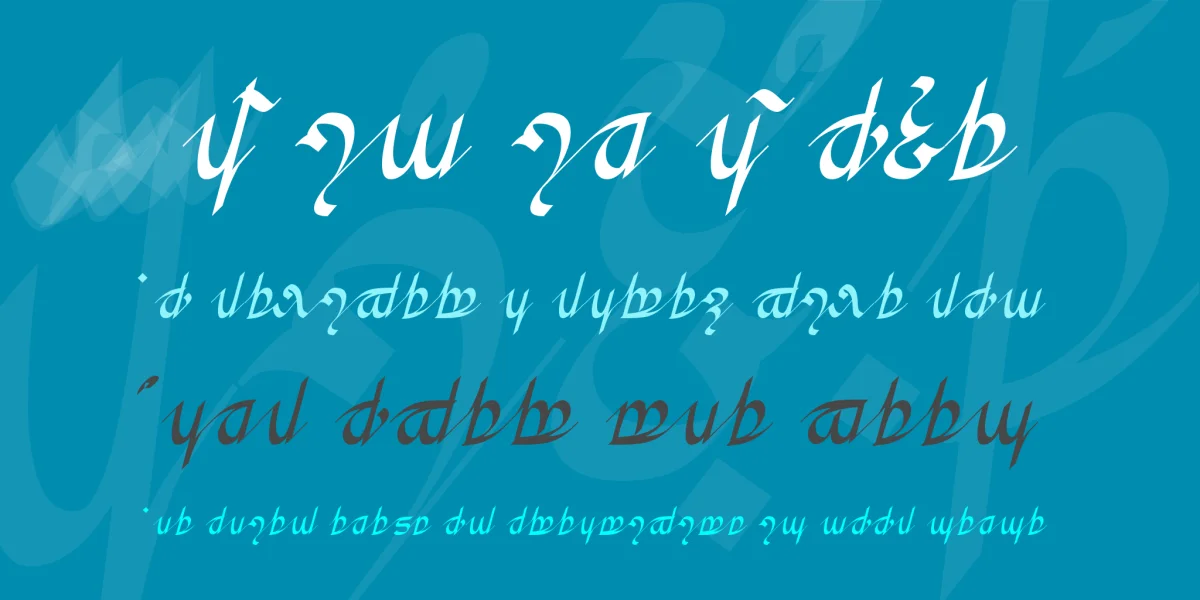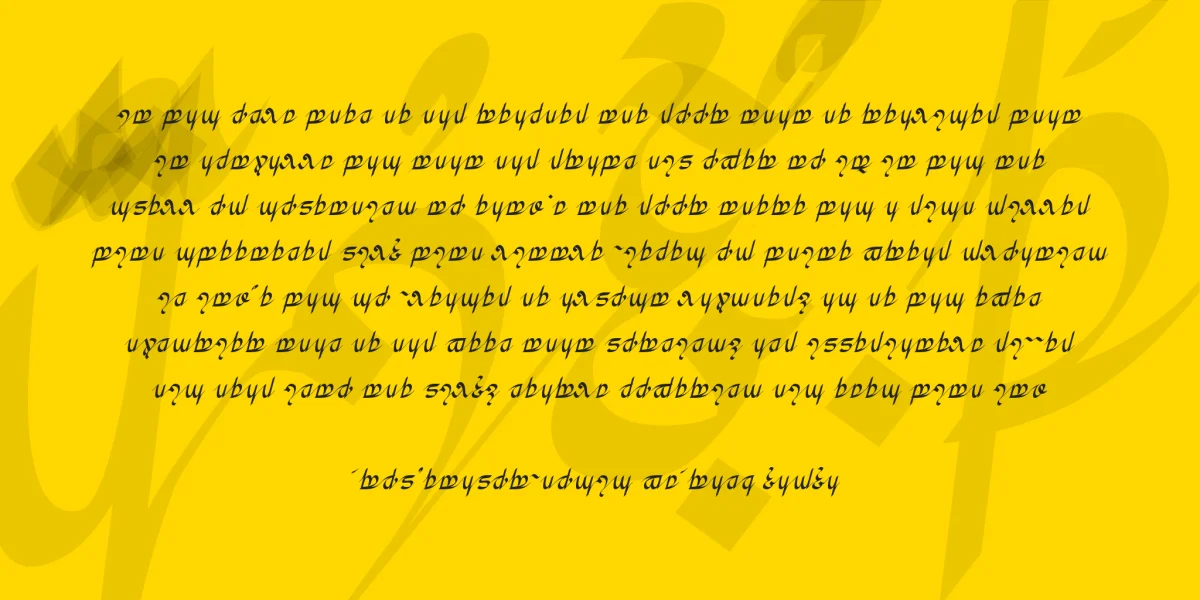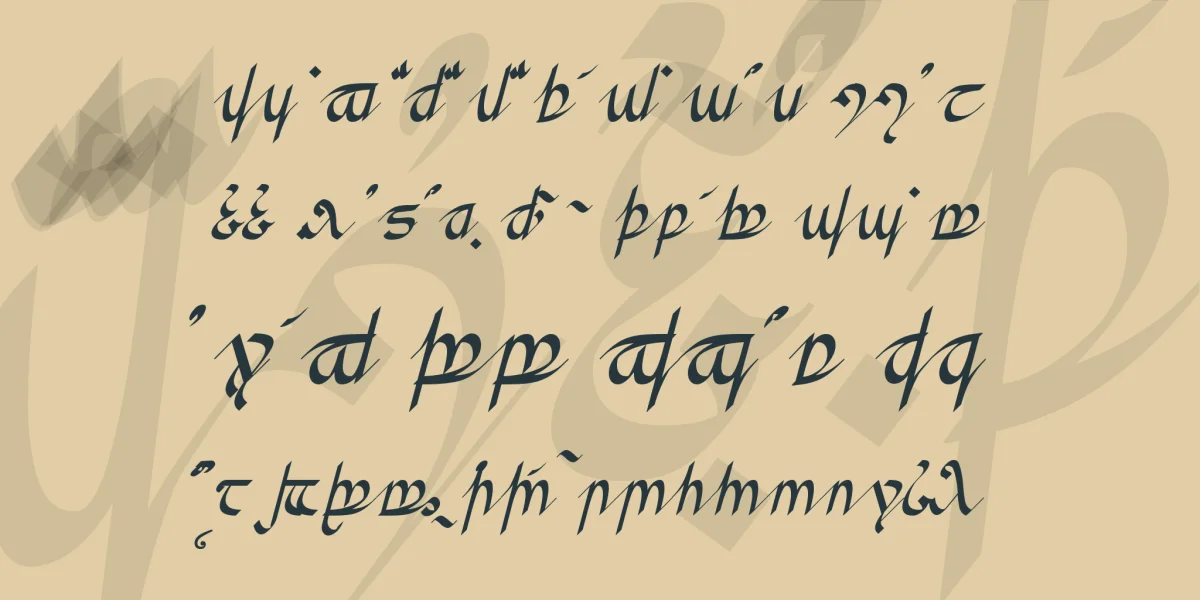
"Ilu Ilúvatar en kár. e eldain a fírimoin ar antarota mannar Valion: Númessier. Toi aina, mána, meldielto – enga morio Talantie. Mardello Melko lende: Márie." - Auf deutsch: "Der Vater schuf die Welt für Elben und Sterbliche, und er gab sie in der Hände der Herren: Sie sind im Westen. Sie sind heilig, gesegnet und geliebt: außer dem Dunklen: Er ist gefallen. Melko ist von der Erde gegangen: Es ist gut." lauten die ersten Sätze aus Fíriels Lied aus Tolkiens Buch "The Lost Road" den ich hier als Quenja-Mustertext ausgewählt habe.
Neben der Elbic Calslon ist dies meine zweite Tengwar-Schrift, der von J.R.R. Tolkien erfundenen Schrift seiner Kunstsprache für seine Mythenwelt. Auch diese Schrift folgt wieder der mittlerweile als Standard etablierten Belegung nach Daniel S. Smith, wodurch diese Schrift mit "The Tengwar Scribe" genutzt werden kann.